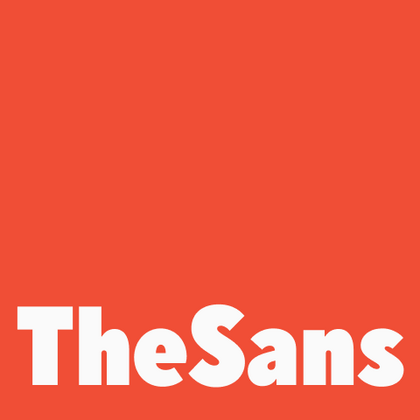
Шрифты похожие на TheSans
Шрифтовая альтернатива: TheSans
Шрифты похожие на TheSans
Профессиональные дизайнеры часто выбирают гуманистические гротески за их баланс дружелюбия и функциональности. В коллекции TypeType вы найдёте современные альтернативы, которые могут заменить шрифт TheSans в ваших проектах. Наши шрифты-аналоги идеально подходят для фирменного стиля и брендинга, веб-дизайна и интерфейсов, деловой полиграфии и многоязычных проектов.
Если вы устали от «заезженных» шрифтов и ищете гарнитуры, похожие на TheSans, ознакомьтесь с нашими лучшими альтернативами TheSans. Это шрифты, которые имеют близкие характеристики, но в то же время обладают новыми уникальными особенностями дизайна. Например, относятся к той же категории шрифтов, подходят для тех же целей и имеют похожие черты, но отличаются в деталях или пропорциях.
Найдите отличную замену TheSans и попытайтесь имитировать похожее настроение, передать нужное вам ощущение, используя его в своих проектах. Каждый шрифт, представленный на этой странице, является двойником шрифта TheSans, фактически его полным аналогом.